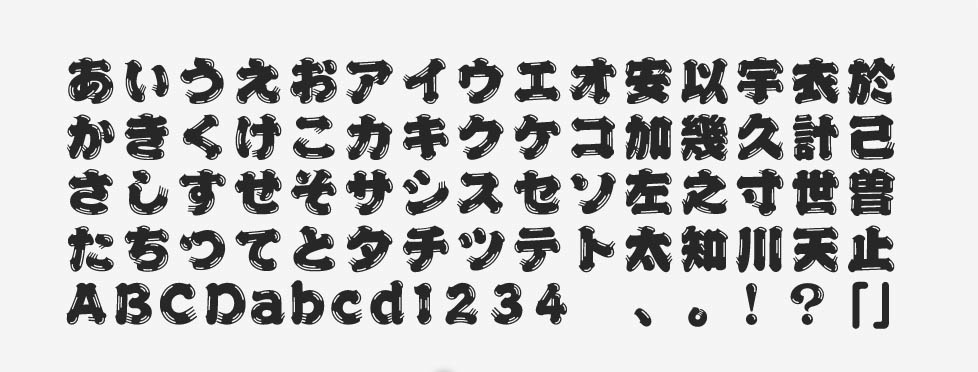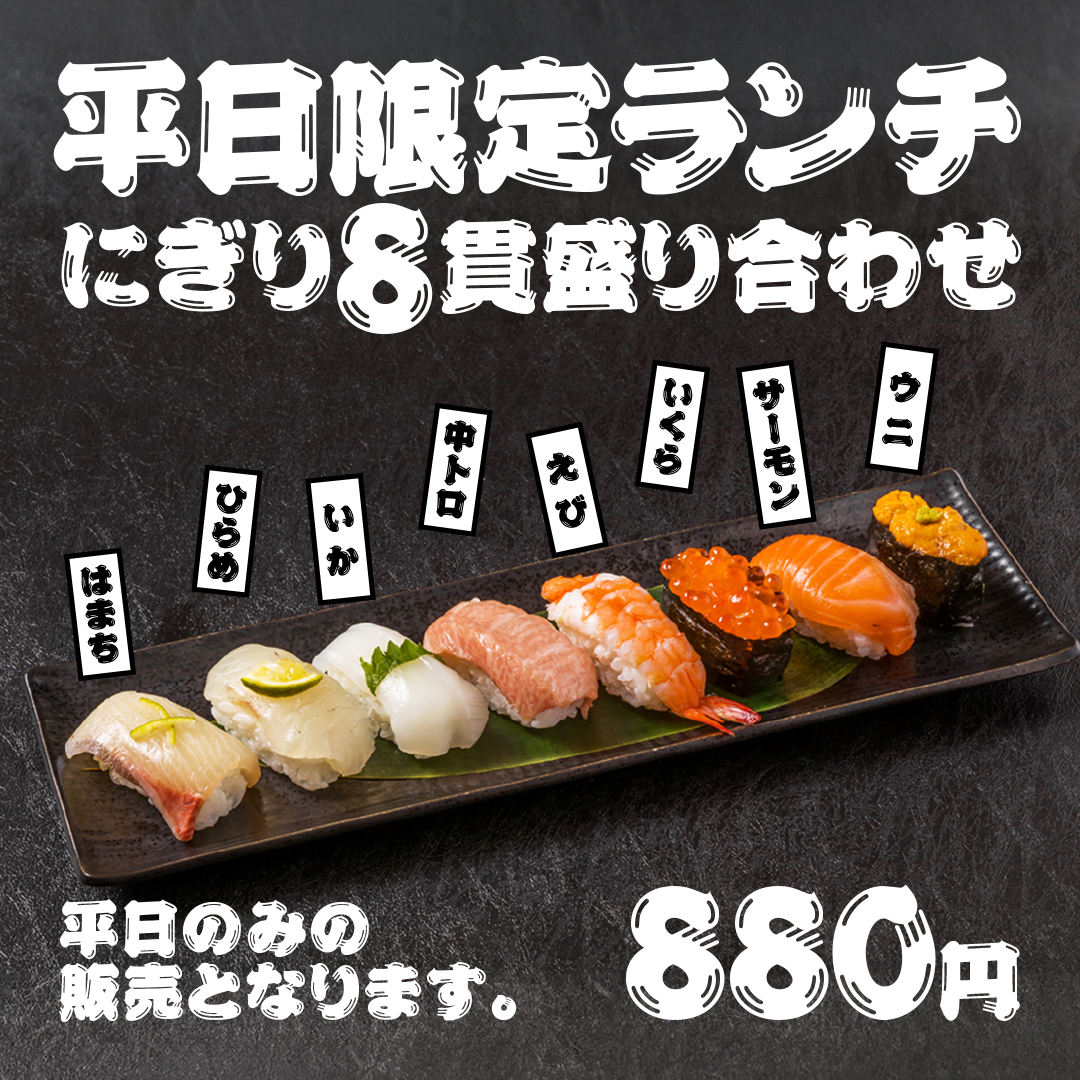
「ひげ文字」について
筆書体の中でも、江戸時代に多く使われた伝統的な図案文字(江戸文字)の1つです。フォントとしてのひげ文字は、1977年にモリサワ写植文字盤用書体としてリリースされた書体を復刻し、デジタル化されています。OpenTypeフォントでの提供は、2014年に開始されました。
「ひげ文字」の特徴
極太の筆で書いたような、絶大な力強さを感じさせるフォントです。墨がかすれたような白い筋で、筆の勢いのよさが感じられます。さらに、終筆部にある複数本の黒い筋も特徴です。「髭」と呼ばれるこの部分にも、墨の名残が残されています。
もともと江戸文字から誕生しているという背景から、和風テイストのデザインに最適です。字面が大きいので活気に満ちた生命力を表現でき、祭りのようなエネルギッシュな賑わいの演出にも役立ちます。
ひげ文字の本来の魅力は、大きめのサイズで発揮されます。同じくモリサワの勘亭流は意外に小さいサイズで特徴を発揮するので、文字サイズに応じてレイアウトの中で使い分けてみても効果的でしょう。ひげ文字は各数字のデザインも秀逸なフォントで、作例のように価格帯が優しめな「和」の価格表示にとても似合います。
題字、コミック、商品パッケージ、ロゴ、ラベル、チラシ、ポスター、POP、看板